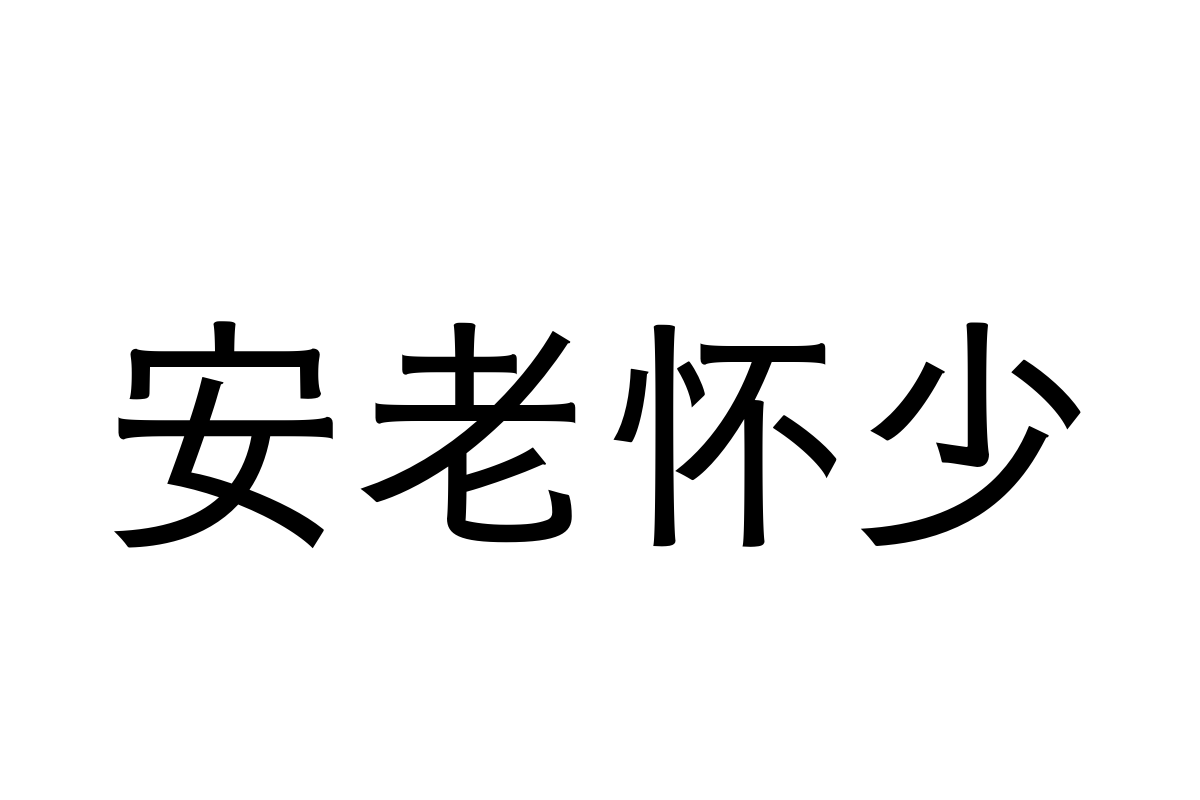
汉仪云黑55w是一款具有现代感和科技感的中文字体。它由汉仪公司设计,采用简洁明了的风格,线条流畅,结构清晰。字体大小为55号,适合用于各种需要强调文字的地方,如标题、标志、广告等。
该字体的特点是字形圆润,笔画粗细适中,既有现代感又不失传统韵味。在设计时,注重保持字形的平衡和对称性,使得整体看起来更加和谐美观。同时,字体还具有一定的可读性,适用于各种场合的文字排版。
总的来说,汉仪云黑55w是一款实用而经典的中文字体,适合用于各种需要强调文字的设计项目。